أفضل 18 خطوط سلتيك لعام 2023 (مجاني ومميز)
نشرت: 2023-07-27هل أنت مصمم جرافيك تتطلع إلى تحسين مشاريعك بلمسة من سحر سلتيك؟ أو ربما تكون جديدًا في عالم خطوط سلتيك وترغب في استكشاف الإمكانيات التي تقدمها؟ حسنًا ، لقد أتيت إلى المكان الصحيح!
في منشور المدونة هذا ، سنغوص في أفضل 18 خطًا سلتيكًا من المؤكد أنها سترفع مستوى لعبة التصميم الخاصة بك. ولكن قبل أن نغامر أكثر ، قد تتساءل - لماذا خطوط سلتيك؟ ما يجعلها الخاصة بذلك؟
الخطوط السلتية مستوحاة من الثقافة السلتية القديمة ، والمعروفة بتشكيلاتها المعقدة ، واللوالب ، والأنماط النابضة بالحياة. إنها تضفي طابعًا فريدًا وجذابًا على أي تصميم ، سواء كان شعارًا أو دعوة أو موقعًا إلكترونيًا.
بفضل تاريخها الغني وأهميتها الثقافية ، اكتسبت خطوط سلتيك شهرة في مجتمع التصميم ، حيث تقدم مجموعة واسعة من الأساليب والاختلافات للاختيار من بينها.
في هذه المقالة ، لن نعرض أفضل 18 خطًا سلتيكًا فحسب ، بل سنزودك أيضًا ببعض الإحصائيات والحقائق المثيرة للاهتمام حول كل خط.
ستتعرف على أصولها وميزاتها المميزة وكيف يمكن دمجها بشكل فعال في مشاريع التصميم الخاصة بك. لذا استعد للشروع في رحلة عبر العالم الآسر لخطوط سلتيك واكتشف الشكل المثالي لرفع تصميماتك. دعنا نتعمق!
أفضل الخطوط سيلتيك قسط
تبحث لإضافة بعض الذوق السلتي لمشاريع التصميم الخاصة بك؟ لا مزيد من البحث! في هذا القسم ، اخترنا يدويًا أفضل خطوط سلتيك المتميزة التي ستأخذ تصميماتك إلى المستوى التالي. لا تفوّت هذه الخطوط الرائعة - تحقق منها واحصل على الإلهام!
سركان
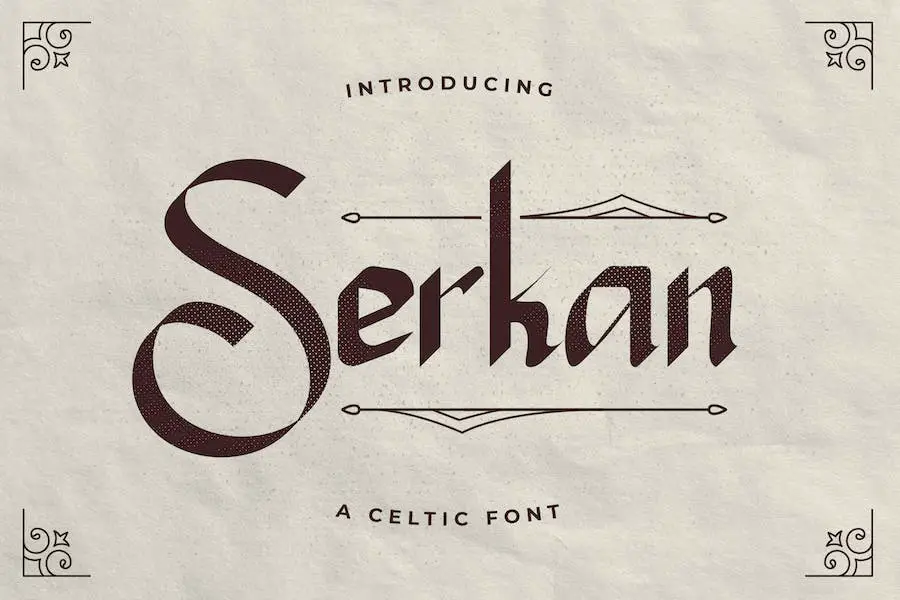
Serkan هو خط سلتيك حديث مستوحى من الأساليب الجذابة والمعقدة للفن السلتي. إنه يوفر مظهرًا فريدًا وأصليًا مثاليًا لمختلف المشاريع الإبداعية.
سواء أكنت بحاجة إلى إنشاء ترويسة مذهلة أو عناوين جذابة أو أدوات مكتبية أنيقة ، فمن المؤكد أن هذا الخط سيضيف لمسة من الأناقة والرقي إلى تصميماتك.
مع تصميمه المعقد المستوحى من سلتيك ، يتميز Serkan عن غيره من الخطوط. أسلوبه المفصل والآسر يجعله مثاليًا لإضافة لمسة من السحر والشخصية إلى مشاريعك.
سواء كنت تعمل على شعار أو ملصق أو حتى دعوة زفاف ، فإن هذا الخط سيرفع من تصميمك على الفور.
واحدة من السمات الرئيسية لـ Serkan هي تنوعها. يمكن استخدامه لمجموعة واسعة من الأفكار المبتكرة ، من الترويسات الاحترافية إلى القرطاسية المرحة. يتيح لك المظهر الفريد والأصلي للخط إطلاق العنان لإبداعك وإبراز تصميماتك حقًا.
قلعة الملك
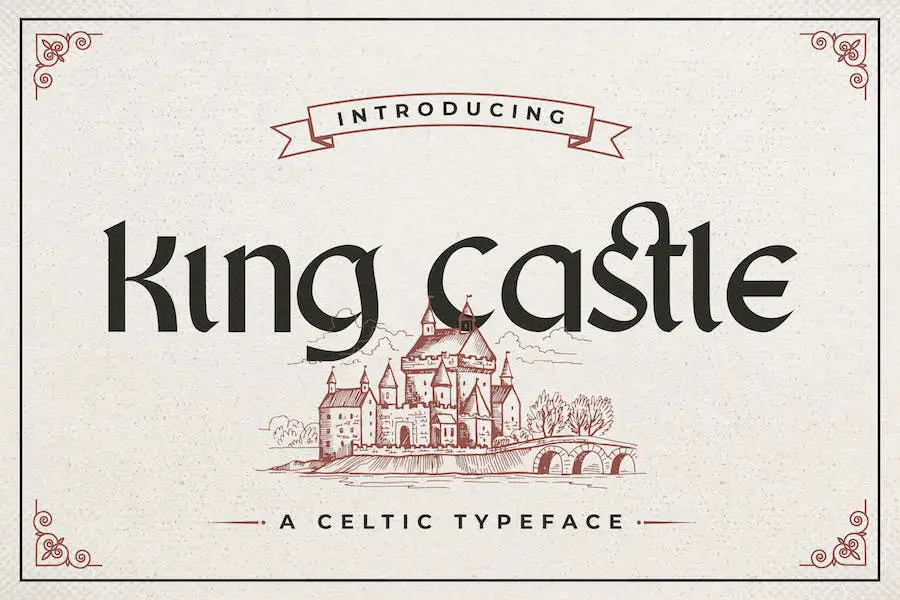
King Castle هو خط ذو طراز سلتيك أنيق يضفي لمسة من السحر السلتي على مشاريع التصميم الخاصة بك. مستوحى من الأنماط السلتية المعقدة ، يعد محرف العرض الفريد هذا مثاليًا لإضافة لمسة شخصية وشخصية إلى مشاريعك.
بمظهرها الأصلي ، تعد King Castle خيارًا رائعًا لمجموعة واسعة من الأفكار المبتكرة. سواء كنت تصمم أوراقًا ذات رأسية ، أو تنشئ عناوين جذابة ، أو حتى تصمم قرطاسية ، فإن هذا الخط سيساعد مشاريعك على التميز عن الآخرين.
يعد تصميم King Castle المستوحى من سلتيك مثاليًا لإضافة لمسة من التاريخ والتقاليد إلى تصميماتك. تجعل تفاصيله المعقدة والفريدة من نوعها خيارًا متعدد الاستخدامات لأي مشروع تريد أن تنقل فيه إحساسًا بالحرفية والتطور.
لاكوست سلتيك
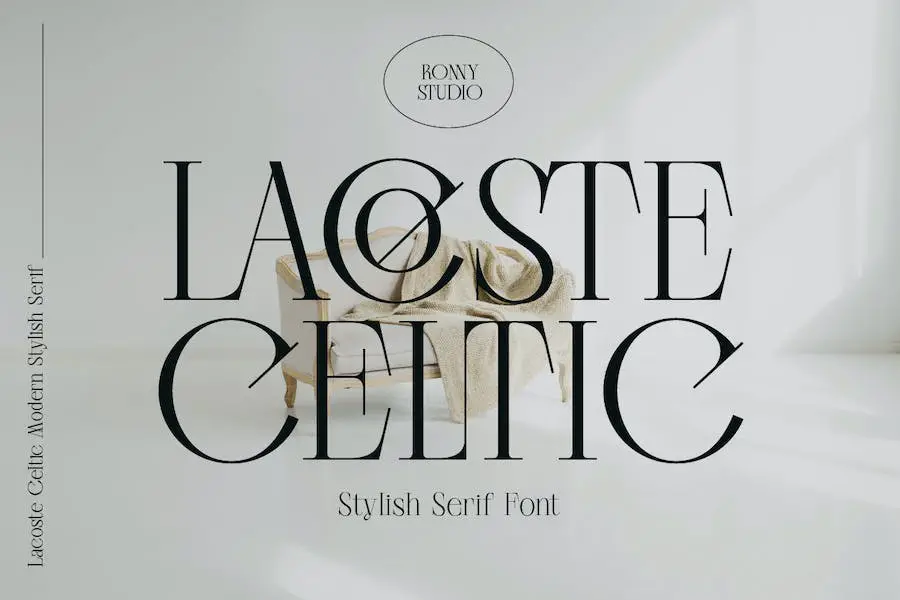
Lacoste Celtic هو خط صممه Ronny Studio ، وهو مثالي لمصممي الجرافيك الذين يتطلعون إلى تحسين مشاريعهم بلمسة سلتيك. يضفي هذا الخط متعدد الاستخدامات سحرًا فريدًا على أي تصميم ، سواء كان شعارًا أو ملصق أو موقعًا إلكترونيًا.
مع Lacoste Celtic ، يمكنك إضافة طابع سلتيك أصيل إلى تصميماتك. التفاصيل المعقدة والمنحنيات الجميلة لهذا الخط تجعله جذابًا وجذابًا بصريًا. إنه مثالي للمشاريع التي تحتاج إلى لمسة من الأناقة والثراء الثقافي.
واحدة من السمات البارزة في Lacoste Celtic هي تنوعها. يمكن استخدامه لكل من المشاريع الشخصية والتجارية ، مما يمنح المصممين حرية استكشاف إبداعاتهم دون قيود.
سواء كنت تعمل على العلامة التجارية للعميل أو تقوم بإنشاء عمل فني لنفسك ، فإن هذا الخط قد جعلك مغطى.
رينج أوف كيري
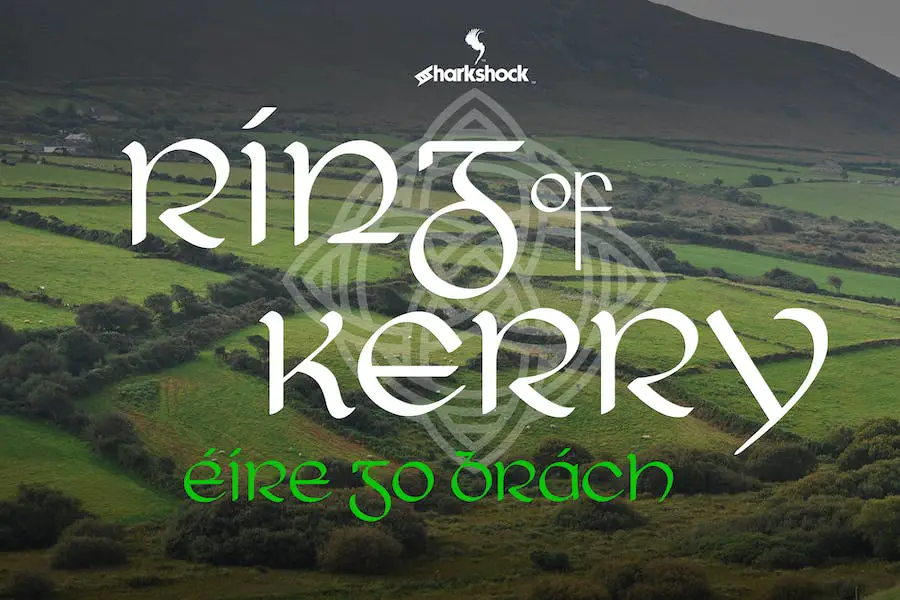
Ring of Kerry هو خط عرض تزييني يجمع بين جمال الكتابة الغيلية في العصور الوسطى والخط غير المقبول مع لمسة من السحر الأيرلندي. تم تصميم الشخصيات التي تعتمد على الدوائر في الغالب لتكرار نفسها وملء الفراغ الأفقي ، مما يجعلها مثالية لمشاريع التصميم المختلفة.
مع كل من الحروف الكبيرة والصغيرة البديلة ، فإنها توفر بعض التنوع والمرونة. وهو يدعم اللغة اللاتينية الأساسية ، وعلامات الترقيم ، واللهجات الأوروبية ، وتقنين الأحرف ، وحتى يتضمن عددًا قليلاً من عقد سلتيك. للوصول إلى هذه الميزات ، ما عليك سوى استخدام لوحة الحروف الرسومية لبرنامجك.
وإذا كان برنامجك لا يدعم ميزات OTF ، فلا يزال بإمكانك الإبداع باستخدام رموز العلامات التجارية مثل و. سواء كنت تصمم بطاقات تهنئة أو ملصقات أو حتى شعار حانة ، فمن المؤكد أن Ring of Kerry سيجلب الابتسامة على وجهك واللحن إلى قلبك.
ترقص
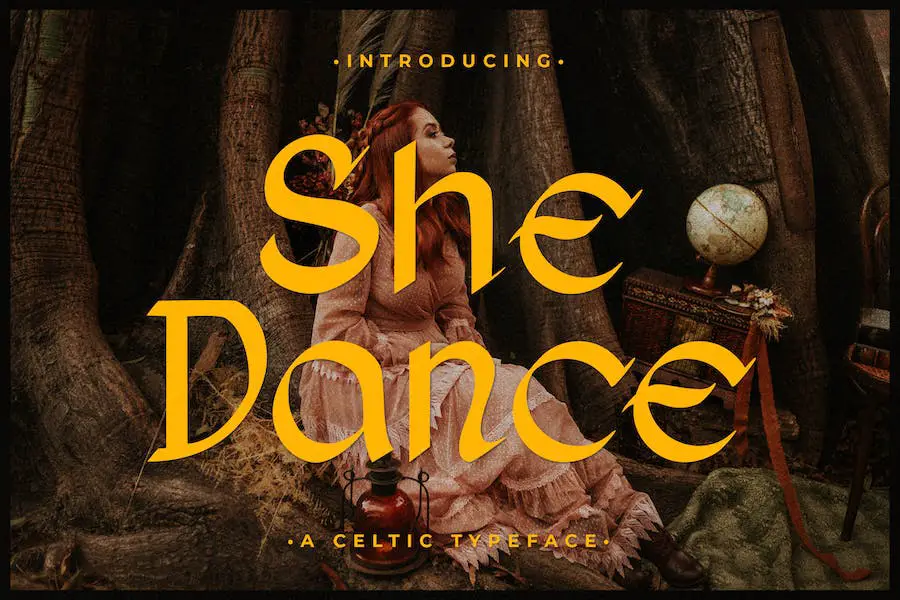
She Dance هو خط عرض حديث وأنيق بنمط سلتيك يجمع بين التقاليد والتطور المعاصر. إنه يضفي لمسة شخصية وجمالية على أي مشروع تصميم ، مستوحى من أنماط سلتيك.
سواء كنت تعمل على شعار أو علامة تجارية أو أي مسعى إبداعي آخر ، فإن She Dance هو الخيار الأمثل لإضافة عنصر فريد وجذاب إلى عملك.
بفضل تصميمه الحديث ومظهره الشخصي ، من المؤكد أنه خط مثير للإعجاب. لذا ، إذا كنت تبحث عن خط سلتيك قديم مع لمسة عصرية ، فلا تنظر إلى أبعد من She Dance.
أكسيد
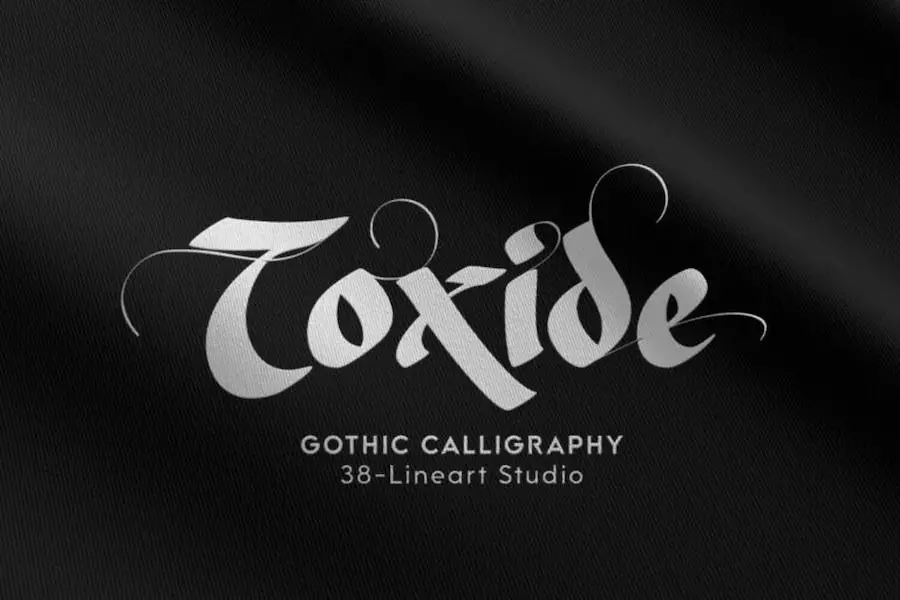
Toxide هو خط قوطي مستوحى من أنماط سلتيك وأنكيال. بلمسة فريدة ، يعد خط العرض هذا مثاليًا لتعزيز العلامات التجارية والشعارات والعناوين الرئيسية والشارات وعناوين الفيديو وأغلفة الكتب وأغلفة المجلات.
وهو يدعم التشكيل اللاتيني للحروف الرسومية الأساسية ويقدم 7 مجموعات نمطية ، مما يسمح بإجمالي 1193 حرفًا رمزيًا للاختيار من بينها. تضمن هذه المرونة أنه يمكنك العثور على الصورة الرمزية المثالية التي تناسب احتياجات التصميم الخاصة بك.
سواء كنت مصمم جرافيك أو ترغب ببساطة في رفع مستوى جماليات مشاريعك ، فإن Toxide هو خط لا بد منه في مجموعتك. إنه مثالي لأولئك الذين يقدرون جمال التصميم السلتي ويريدون دمجه في عملهم. امنح تصميماتك لمسة من الأناقة السلتية باستخدام Toxide.
بريكيوس
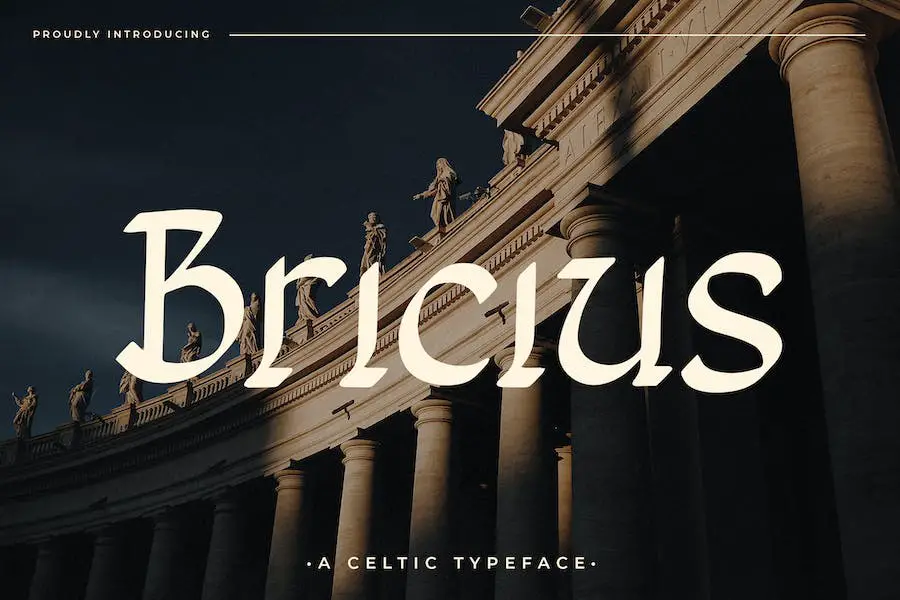
Bricius هو خط أنيق وعصري يجمع بين الأسلوب السلتي والتصميم المعاصر. يستمد محرف العرض الفريد هذا الإلهام من جماليات سلتيك ، مما يمنح مشاريع التصميم الخاصة بك لمسة شخصية وجمالية.
سواء كنت تعمل على تصميم شعار أو تصميم موقع ويب أو أي مشروع آخر يتطلب مظهرًا مميزًا ، سيضيف Bricius تلك اللمسة الإضافية من الأناقة والإبداع.
بمظهره الحديث والشخصي ، يعد هذا الخط مثاليًا لإنشاء تصميم آسر لا يُنسى. ارتق بمشاريعك إلى المستوى التالي مع Bricius ودع إبداعك يتألق!
يسحر
Enchant هو محرف مستوحى من سلتيك من القرن السابع عشر وهو مثالي لإضافة لمسة من السحر إلى مشاريع التصميم الخاصة بك. إن خط الخط هذا ليس مقروءًا فحسب ، ولكنه مميز أيضًا بشكل جميل.
مع Enchant ، يمكنك إنشاء أغلفة كتب رائعة ، منشورات جذابة على وسائل التواصل الاجتماعي ، تخطيطات مذهلة للمجلات ، تصميمات عبوات جذابة ، شعارات فريدة ، قمصان عصرية ، تصميمات رمزية ، ملصقات تجذب الأنظار ، وأي شيء آخر يمكن أن يخطر ببالك. .
يجسد تصميمه الأنيق والمعقد جوهر جماليات العصور الوسطى والسلتية ، مما يجعله الخط المثالي إذا كنت ترغب في تكرار هذا المظهر القديم والصوفي. أضف لمسة سحرية على تصميماتك مع Enchant.
كلترا
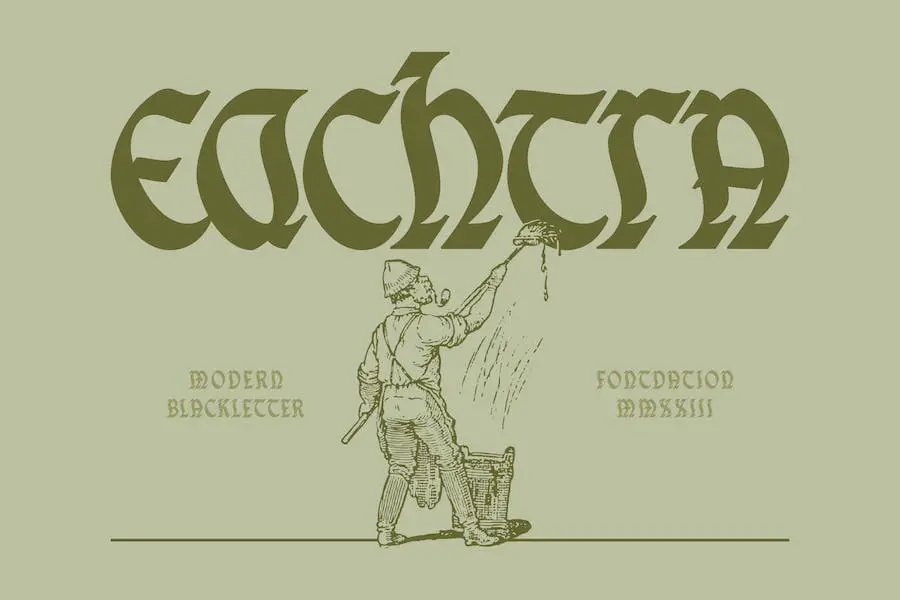
كلترا هو خط أسود صغير حديث يسمى "تقديمه" والذي يتضمن لمسة من الحروف السلتية / الغيلية. هذا الخط مثالي لإنشاء تصميمات ملصقات لافتة للنظر ، وعروض أسعار مؤثرة ، وعناوين تجذب الانتباه.
بمزيجها الفريد من العناصر الحديثة والسلتيك ، يجلب كلترا مظهرًا جديدًا ومميزًا لمشاريع التصميم الخاصة بك.
سواء كنت تعمل في مشروع يحتاج إلى جمالية جريئة وحادة أو ترغب في إضافة لمسة من التراث السلتي إلى تصميماتك ، فمن المؤكد أن كلترا سترفع من إبداعاتك.
ديرصومعة
الدير هو خط سلتيك حديث ينضح بأسلوب عرض ممتع وممتع. بفضل طابعه الفريد الذي يعود إلى العصور الوسطى ، فهو مثالي لإضافة لمسة من التاريخ إلى مشاريعك. مستوحى من نوع حرف ذو مظهر قوطي من العصور الوسطى ، من المؤكد أن هذا الخط سيضفي سحرًا مميزًا على أي تصميم.
إن سمات الدير هي التي تجعله مميزًا حقًا. تضفي التأثيرات السلتية عليها إحساسًا بالغموض والمكائد ، بينما تضيف اللمسة الحديثة لمسة معاصرة.
سواء كنت تعمل في مشروع ذي طابع تاريخي أو تريد ببساطة إضافة بعض السمات إلى تصميماتك ، فإن Monastery هو الخط المناسب لك.
هذا الخط متعدد الاستخدامات ويمكن استخدامه في سياقات مختلفة. من الملصقات وأغلفة الكتب إلى التصميمات الرقمية والشعارات ، يمكن لـ Monastery تحسين أي تمثيل مرئي لأفكارك.
إنه خط يجمع بسهولة بين القديم والجديد ، مما يجعله الخيار الأمثل لأولئك الذين يرغبون في الإدلاء ببيان مع تصميماتهم.
خليف
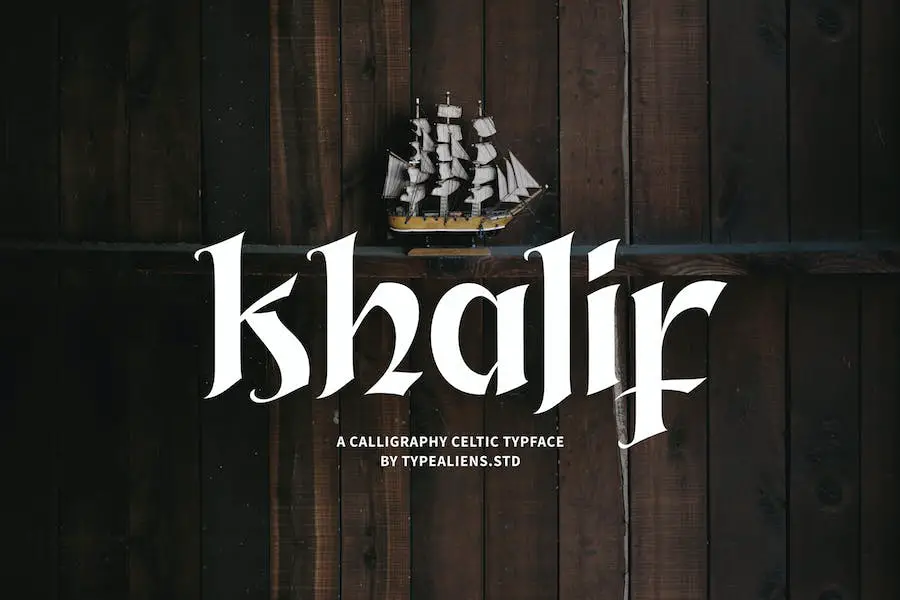
KHALIF هو خط محرف مستوحى من الطراز القديم مستوحى من أنماط سلتيك وأنسيال. إنه يوفر مظهرًا فريدًا ومميزًا ، مما يجعله مناسبًا للتصميمات التي تتضمن رسومًا توضيحية أو ذات طابع كلاسيكي.
هذا الخط مناسب بشكل خاص للاستخدام في العناوين الرئيسية والشعارات وتصميم الشارات ، فضلاً عن عناوين الأفلام والكتب والمجلات.
مع تصميمه المتأثر بالفارسية والتركية ، يضيف خليف لمسة من الذوق الثقافي إلى أي مشروع. سواء كنت تعمل على ملصق أو غلاف كتاب أو تخطيط مجلة ، سيساعدك هذا الخط في إنشاء تصميمات جذابة وملفتة للنظر.
تنوعها يسمح لها بالتكيف مع أنماط وأنواع التصميم المختلفة.
تضيف جمالية KALIF القديمة سحر الحنين إلى الماضي لمشاريعك ، مما يثير الإحساس بالتاريخ والتقاليد. تجعله ميزاته الأنيقة والزخرفية مثالية لإنشاء شعارات مذهلة أو مواد للعلامات التجارية.
إنه خيار رائع للمصممين الذين يرغبون في إضافة لمسة من الرقي إلى عملهم.
فوردير
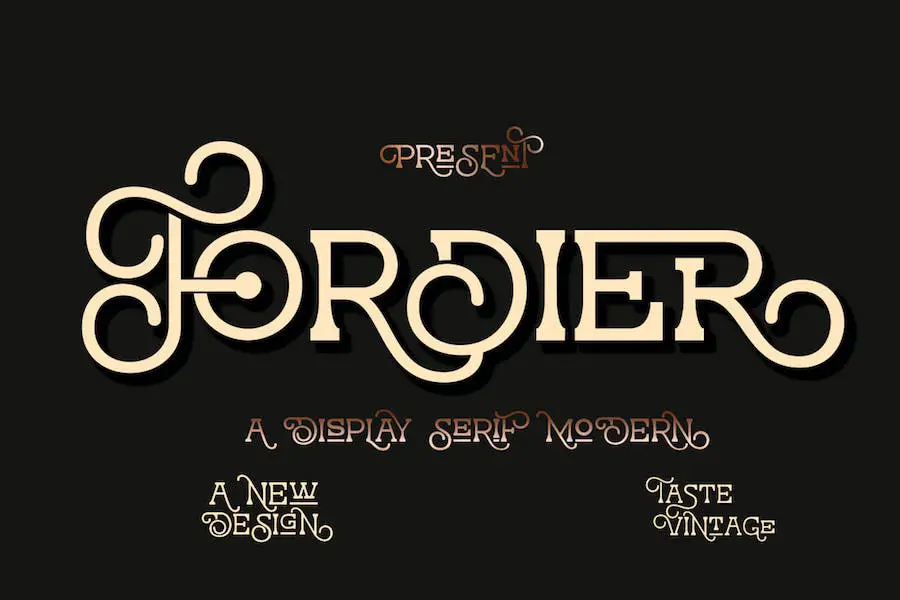
Fordier هو خط سلتيك حديث ينضح بالسحر والأناقة. بفضل تصميمه الأنيق والمتطور ، يعد هذا الخط مثاليًا لتحسين جميع أنواع المشاريع ، من التصميمات والعناوين إلى أغلفة الكتب والدعوات.
تضيف الأحرف البديلة للخط لمسة شخصية ، مما يسمح للمستخدمين بإنشاء تصميمات فريدة وجذابة. سواء كنت تعمل على عناوين أفلام ، أو منشورات على وسائل التواصل الاجتماعي ، أو ملصقات ، أو تصنع مظهرًا مستوحى من الطراز القديم ، فإن Fordier قد جعلك مغطى.
ميزة أخرى رائعة هي أن الخط تم ترميزه باستخدام PUA ، مما يجعل من السهل الوصول إلى واستخدام جميع الأحرف والحروف الرسومية. تنوعها وجاذبيتها الكلاسيكية تجعلها ضرورية لأي مصمم جرافيك أو فرد مبدع. فلماذا لا تضيف لمسة من السحر السلتي إلى مشروعك القادم مع Fordier؟
أفضل الخطوط السلتية المجانية
تبحث لإضافة لمسة من سحر سلتيك إلى تصاميمك؟ لا مزيد من البحث! من المؤكد أن مجموعتنا المكونة من أفضل 18 خطًا سلتيكًا ستلهم وترتقي بمشاريعك. سواء كنت تصمم شعارًا أو تنشئ دعوة أو تعمل على موقع ويب ، فإن هذه الخطوط ضرورية في مجموعة أدوات التصميم الخاصة بك.
فهيا ، انطلق واكتشف الخط السلتي المثالي الذي سيجعل رؤيتك الإبداعية تنبض بالحياة!
يد سلتيك
Celtic Hand هو خط فريد ومثير للإعجاب ابتكره ديتر ستيفمان. إنه يجسد جوهر الثقافة السلتية وهو مثالي لمصممي الجرافيك الذين يتطلعون إلى تحسين مشاريعهم بلمسة من التصميم السلتي.
بفضل أشكال الحروف المعقدة والأنيقة ، تضيف Celtic Hand إحساسًا بالغموض والأصالة إلى أي تصميم.
تم تصميم هذا الخط بشكل جميل ، حيث تم تصميم كل حرف ليشبه الخط السلتي التقليدي. التفاصيل المعقدة والتشكيلات المعقدة تجعله متميزًا عن الخطوط الأخرى ، مما يمنح تصميماتك مظهرًا فريدًا من نوعه.
سواء كنت تعمل على شعار أو ملصق أو موقع ويب ، ستضفي Celtic Hand لمسة من سحر وسحر سلتيك.
ميزة أخرى لـ Celtic Hand هي توافقها مع برامج التصميم الشائعة مثل Adobe. يمكنك بسهولة دمج هذا الخط في مشاريعك الحالية دون أي متاعب.
كما أنه يعمل بشكل جيد مع محرّر مستندات Google ، مما يجعله خيارًا مناسبًا للمصممين الذين يفضلون أدوات التصميم المستندة إلى مجموعة النظراء.
سلتيك جاليج
Celtic Gaelige هو خط مذهل يمكنه تحسين تصميم مشاريعك بشكل كبير. يعتبر خط Old Celtic ، الذي ابتكرته Susan K. Zalusky ، مثاليًا لمصممي الجرافيك الذين يبحثون عن محرف فريد وملفت للنظر.
مع حروفها المعقدة والمزخرفة المستوحاة من سلتيك ، تضيف Celtic Gaelige لمسة من الأناقة والغموض إلى أي تصميم.
سمات سلتيك غيليج رائعة حقًا. يتميز الخط بالعقد والدوامات المعقدة التي تذكرنا بالأعمال الفنية السلتية القديمة. تضفي الحرفية المفصلة للحروف إحساسًا بالتقاليد والتاريخ لتصميماتك.
سواء كنت تعمل على شعار أو ملصق أو موقع ويب ، فإن Celtic Gaelige ستأسر جمهورك بلا شك.
لا يمتلك Celtic Gaelige جمالية آسرة فحسب ، بل إنه متعدد الاستخدامات أيضًا. يتوفر الخط بأوزان وأنماط مختلفة ، مما يتيح لك تحقيق المظهر المثالي لمشروعك.
سواء كنت تريد عرضًا جريئًا ومؤثرًا أو مظهرًا أكثر دقة وتطورًا ، يمكن لـ Celtic Gaelige التكيف بسهولة مع احتياجاتك.
سلتيك جاراموند الثاني
Celtic Garamond the 2nd هو خط مجاني تم إنشاؤه بواسطة No Images Fonts. إنه خيار مثالي لمصممي الجرافيك الذين يبحثون عن خط سلتيك قديم لتحسين مشاريعهم. بفضل تصميمه الفريد والمعقد ، يضيف هذا الخط لمسة من الأصالة والأناقة إلى أي تصميم.
سواء كنت تعمل على ملصق أو شعار أو موقع ويب ، فمن المؤكد أن Celtic Garamond الثاني سيثير إعجابك. وأفضل ما في الأمر أنه مجاني للاستخدام الشخصي ، مما يسمح لك بالتجربة وإطلاق العنان لإبداعك دون أي قيود.
لا تفوت فرصة دمج هذا الخط المذهل في مشروعك القادم ومنحه طابع سلتيك الخالد.
كايد
Cayed هو خط سلتيك قديم تم إنشاؤه بواسطة Allouse.Studio. إنه يجسد جوهر التصميم السلتي ويضفي لمسة من الغموض القديم على مشاريعك الرسومية.
بفضل تفاصيله المعقدة وأشكاله الفريدة من نوعها ، يعد Cayed الخيار الأمثل لمصممي الجرافيك الذين يتطلعون إلى تحسين تصميماتهم بأسلوب سلتيك.
يتميز هذا الخط بمجموعة كبيرة من السمات التي تجعله متميزًا عن غيره. تضيف حروفه المزخرفة والمعقدة لمسة من الأناقة والرقي لأي مشروع.
سواء كنت تصمم وشمًا أو شعارًا أو حتى ملصق ، فإن أسلوب Cayed المستوحى من Celtic سيجلب إحساسًا بالجمال الخالد لعملك.
واحدة من السمات الرئيسية لـ Cayed هي تنوعها. يمكن استخدامه لمجموعة متنوعة من أغراض التصميم ، من العناوين الرئيسية والعناوين إلى النص الأساسي والعناصر الزخرفية. مع مجموعة واسعة من أشكال وأنماط الحروف ، يوفر هذا الخط إمكانيات لا حصر لها للتعبير الإبداعي.
TF - الغيلية
TF - Gaelic من Twicolabs هو خط رائع يجسد جوهر التصميم الأيرلندي والسلتي القديم. بفضل أشكاله المعقدة والفريدة من نوعها ، يعد هذا الخط مثاليًا لمصممي الجرافيك الذين يرغبون في إضافة لمسة من الذوق السلتي إلى مشاريعهم.
TF - Gaelic يجلب إحساسًا بالتاريخ والثراء الثقافي لأي تصميم ، مما يجعله ضروريًا لأولئك الذين يسعون إلى الارتقاء بعملهم.
سمات الخط رائعة حقًا. تنضح حروفه المفصلة بدقة بجو من الأصالة ، وينقل المشاهدين إلى العصور السلتية القديمة.
TF - منحنيات وخطوط Gaelic المصممة بعناية تخلق نتيجة مذهلة وجذابة بصريًا ، مما يجعلها مثالية للعناوين الرئيسية والشعارات وعناصر التصميم البارزة الأخرى.
بفضل جمالياتها القوية والجريئة ، تستحوذ TF - Gaelic على الاهتمام وتبرز من بين الحشود.
سمالبورج
Smallburg هو خط رائع يحتاجه كل مصمم جرافيك في مجموعة أدواتهم. مع تصميمه السلتي القديم ، يضيف هذا الخط لمسة من الأناقة والتفرد لأي مشروع. إنه يجسد تمامًا روح ثقافة سلتيك ويجلب إحساسًا بالتاريخ لتصميماتك.
سمات سمالبورغ تميزها عن الخطوط الأخرى. تضيف تفاصيله المعقدة والمزخرفة تأثيرًا مرئيًا مذهلاً على عملك ، مما يجعله مناسبًا لمشاريع التصميم المختلفة مثل الشعارات والملصقات والدعوات.
تخلق الخطوط الدقيقة والمنحنيات للحروف إحساسًا بالحركة والتدفق ، مما يضيف لمسة من الطاقة الديناميكية إلى تصميماتك.
واحدة من السمات البارزة في Smallburg هي تنوعها. يمكن استخدامه في كل من الإعدادات التقليدية والحديثة ، مما يوفر مجموعة واسعة من الإمكانيات الإبداعية. سواء كنت ترغب في إنشاء تصميم مستوحى من الطراز القديم أو قطعة معاصرة ، فإن هذا الخط يجعلك مغطى.
أسئلة مكررة
خطوط سلتيك هي محارف مستوحاة من الفن التقليدي لشعب سلتيك ، والذي يتضمن أنماطًا معقدة وأعمالًا متشابكة. تتميز هذه الخطوط بعناصر تصميمها الفريدة ويمكن استخدامها لإضافة لمسة من الثقافة السلتية إلى مشاريع التصميم الخاصة بك.
يمكن استخدام خطوط سلتيك في العديد من مشاريع التصميم ، مثل الشعارات والملصقات والدعوات والوشم والمزيد.
يمكنهم إضافة لمسة من تراث سلتيك وخلق جمالية جذابة بصريا. بمجرد تنزيل خط سلتيك ، يمكنك تثبيته على جهاز الكمبيوتر الخاص بك واستخدامه في برامج التصميم مثل Adobe Photoshop أو Illustrator.
يمكن أن يختلف مدى توفر وترخيص خطوط سلتيك. بعض خطوط سلتيك مجانية للاستخدام الشخصي ، بينما قد يتطلب البعض الآخر ترخيصًا تجاريًا. عند تنزيل خط سلتيك ، تأكد من مراجعة شروط الترخيص التي يوفرها منشئ الخط.
سيساعدك هذا في تحديد ما إذا كان الخط مجانيًا للاستخدام لمشروعك المحدد أو إذا كنت بحاجة إلى شراء ترخيص.
خاتمة
في الختام ، اكتشفنا أفضل 18 خطًا سلتيكًا لتحسين مشاريع التصميم الجرافيكي الخاصة بك. من الأنماط التقليدية إلى الحديثة ، تقدم هذه الخطوط مجموعة من الخيارات لتناسب احتياجاتك الخاصة.
سواء كنت تصمم شعارًا أو موقعًا إلكترونيًا أو أي مشروع إبداعي آخر ، يمكن أن تضيف هذه الخطوط لمسة من سحر سلتيك.